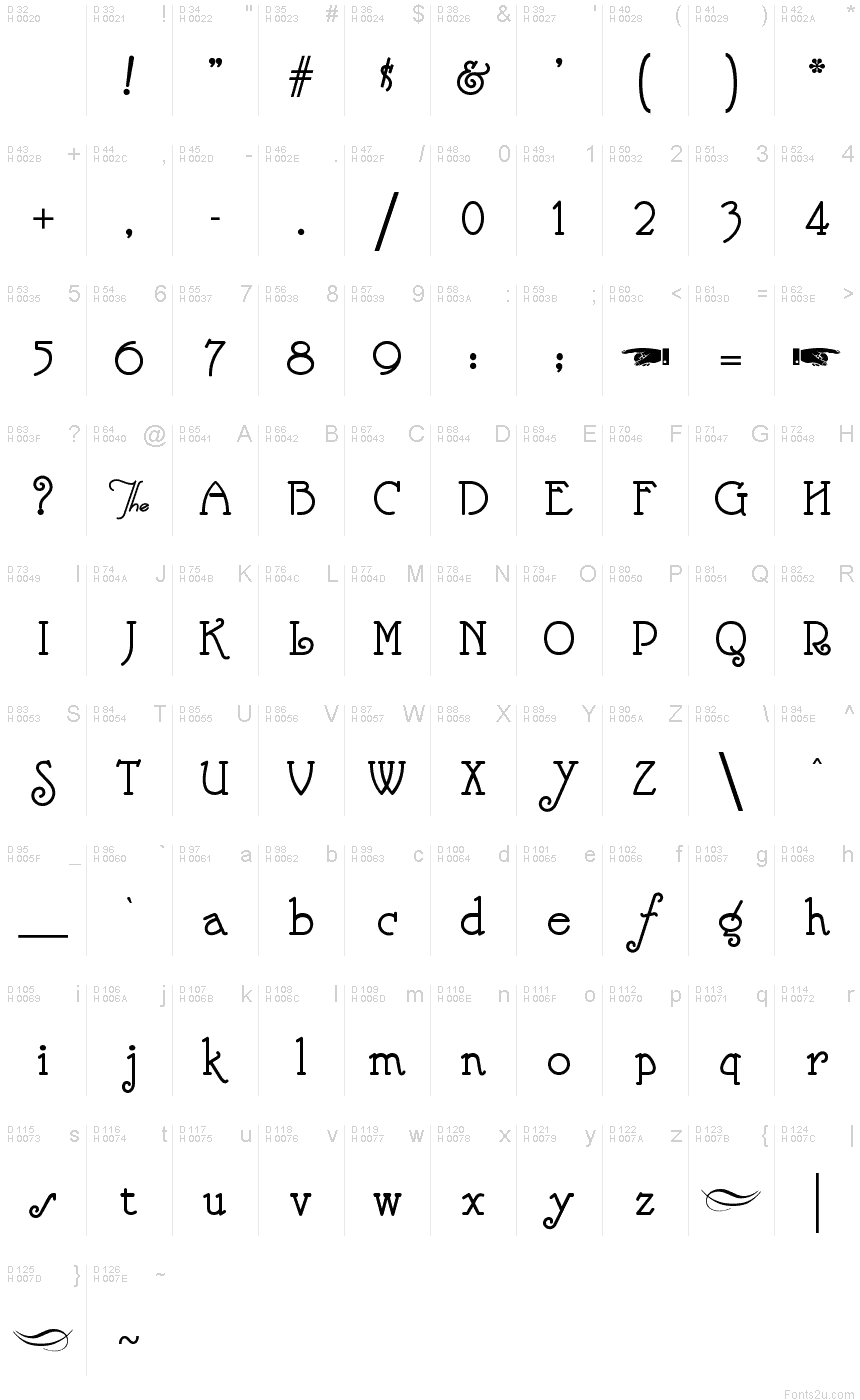
Nickelodeon, bezpłatny retro font typu display autorstwa Nicka Curtisa, czerpie inspirację z reklamowego liternictwa z początku XX wieku, wykorzystując wysokie szeryfy, okrągłe detale i teatralne zawijasy, które nadają całości żywy rytm. Design jest wyprostowany i sceniczny, a nie przesadnie ozdobny; dzięki delikatnie rozszerzanym końcówkom i pętelkom, litery zyskują klimat epoki, pozostając przy tym czytelnymi i przystępnymi.
Takie połączenie sprawdza się idealnie w tytułach na plakatach, menu kawiarnianych, grafikach na etykietach napojów, szyldach sklepowych czy w identyfikacji wizualnej wydarzeń, które mają mieć klimat wodewilu lub starego kina, nie tracąc przy tym na funkcjonalności. Krótkie nagłówki najlepiej wykorzystują potencjał zawiniętych pociągnięć i kompaktowych detali dekoracyjnych; te same cechy świetnie sprawdzą się również na opakowaniach, projektach w stylu biletów czy tematycznych grafikach do mediów społecznościowych.